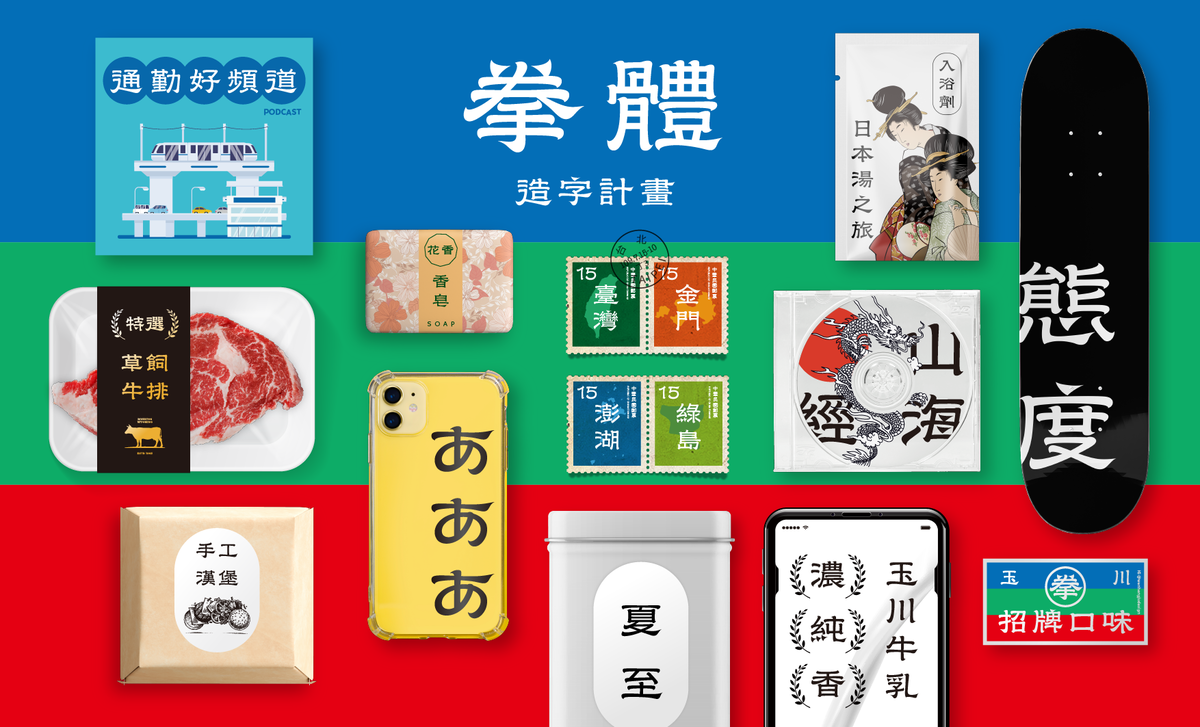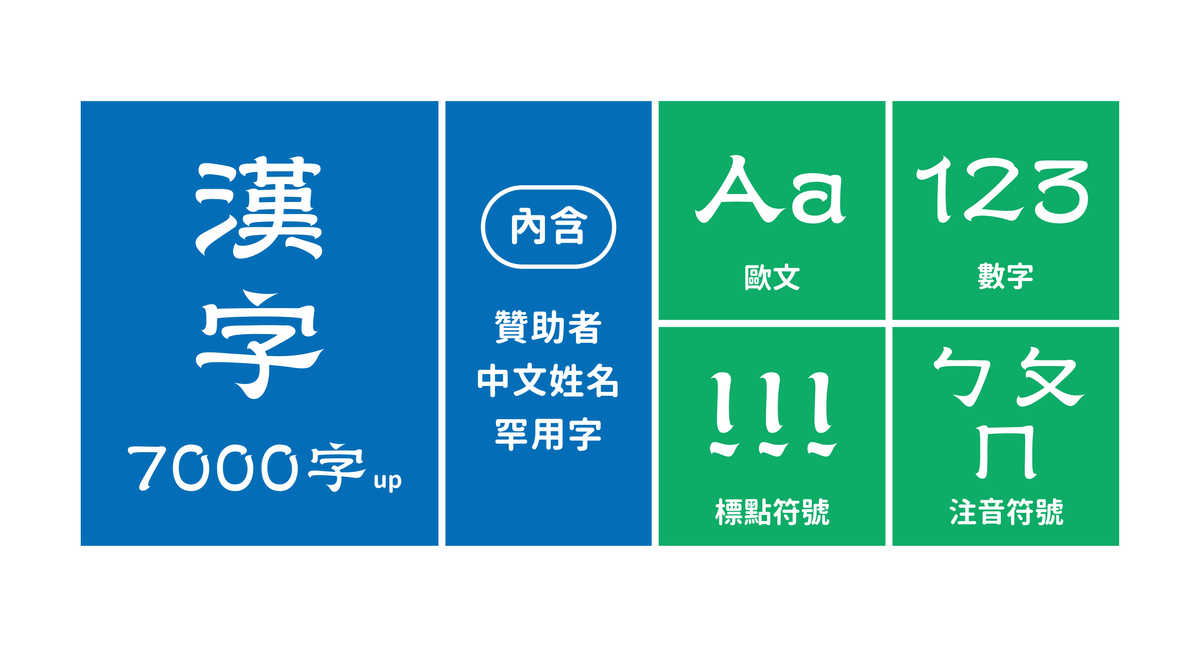
揉和隸書體與臺灣廟宇燕尾造形的字型,
作為字型設計工作者,我想設計出一套造形不生硬、應用性佳的書體。在走訪大稻埕和各個街頭、臺灣廟宇後,決定將招牌很常使用的隸書體結合廟宇建築燕尾曲線,創造帶有臺灣風味的設計字型「拳體」。
希望字型製作完成後,使用者能輕鬆將「拳體」應用在各種場合如:名片、海報、書籍、品牌、包裝、影片,單純放著也很好看很有鮮明的個性和風格。
另外,為了感謝所有朋友的大力支持,「拳體」造字計畫也會將風體贊助者的所有姓名涵蓋在字型製作範圍內,讓所有使用者不因為姓名罕用字而困擾。
✦ 隸書渾厚樸拙的復古美
✦ 融合 #臺灣廟宇建築 的燕尾曲線
✦ 起頭與收尾的俐落感
✦ 筆畫轉折處如拳頭般有力
✦ 打破書法規則 傳統韻味中流露摩登的鋒芒
✦ 大小標題皆適用 #輕鬆應用於多種情境